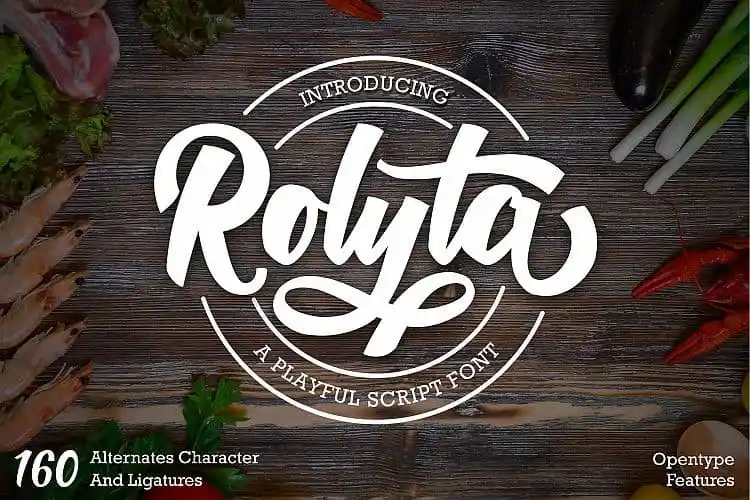
Rolyta Bold Script Font – Download Grátis
Esta é uma fonte script bold brilhante e descontraída. Ela é uma tipografia feita à mão, então você pode encontrar pequenos imperfeições e linhas de base não perfeitamente alinhadas. Tem um toque divertido e animado que faz dela a escolha perfeita para aplicações que valorizam o “cute”. Introduzimos aqui a fonte Rolyta Font, que foi projetada e compartilhada pela Slametype. A Rolyta Playful Bold Script é uma fonte script bold com muitos alternativos de maiúsculas e minúsculas mais do que suficientes, bem como algumas ligaturas. A Rolyta Script é uma opção ótima para vários tipos de projeto, desde logos e identidades visuais até convites, notas de estação, designs de casamento, postagens na mídia social, anúncios, embalagens de produtos, design de produto, etiquetas, fotografia, marca d’água, eventos especiais ou qualquer coisa.